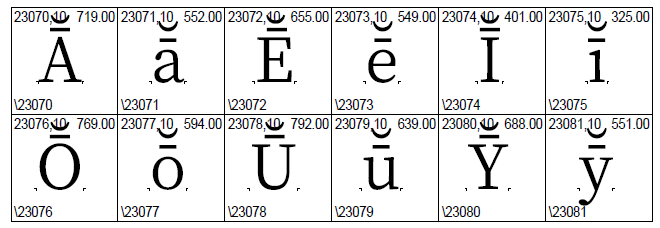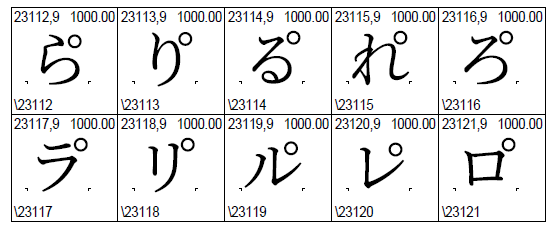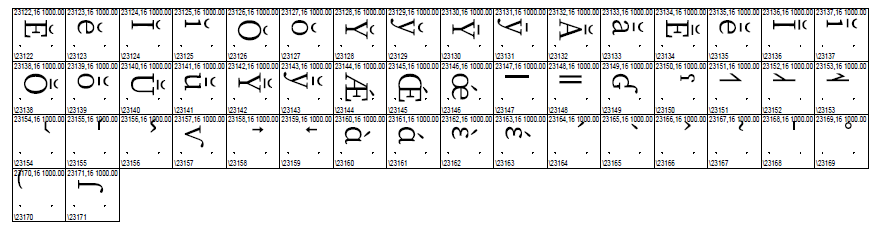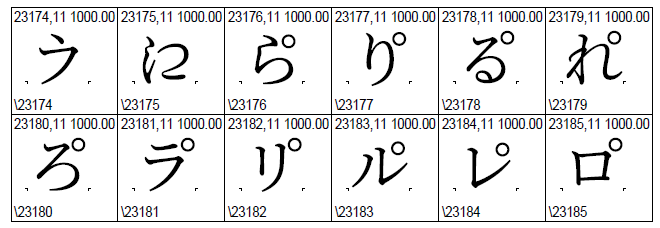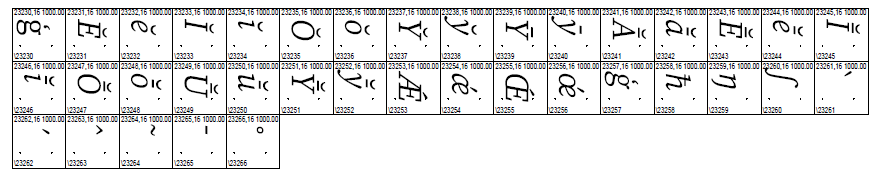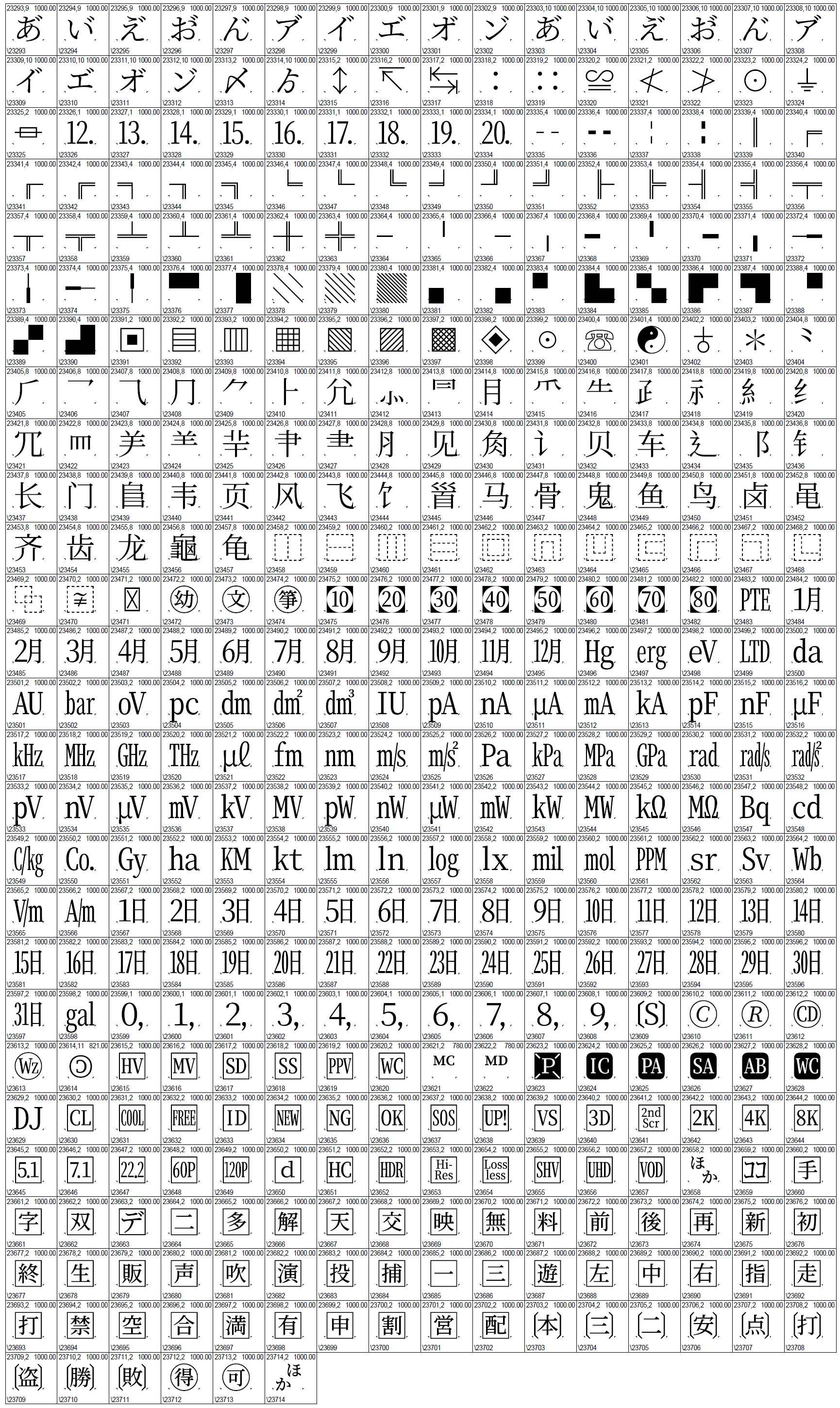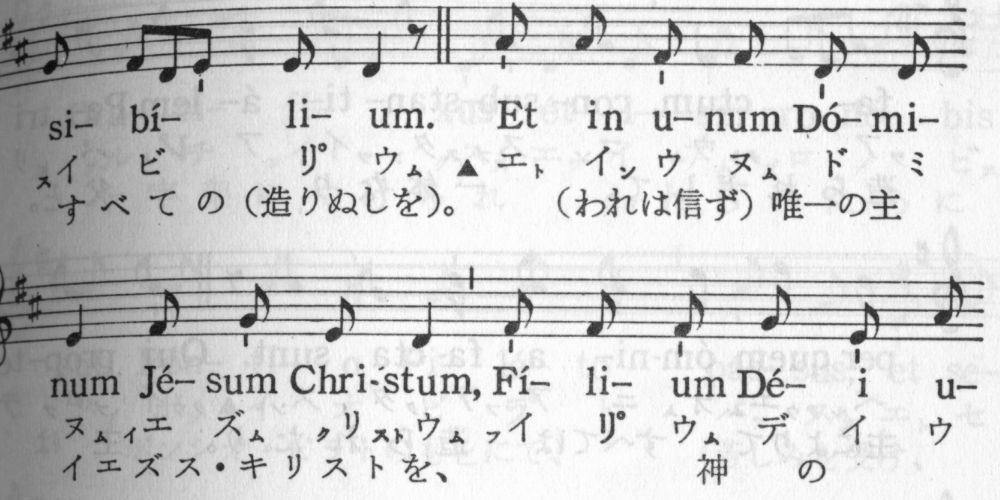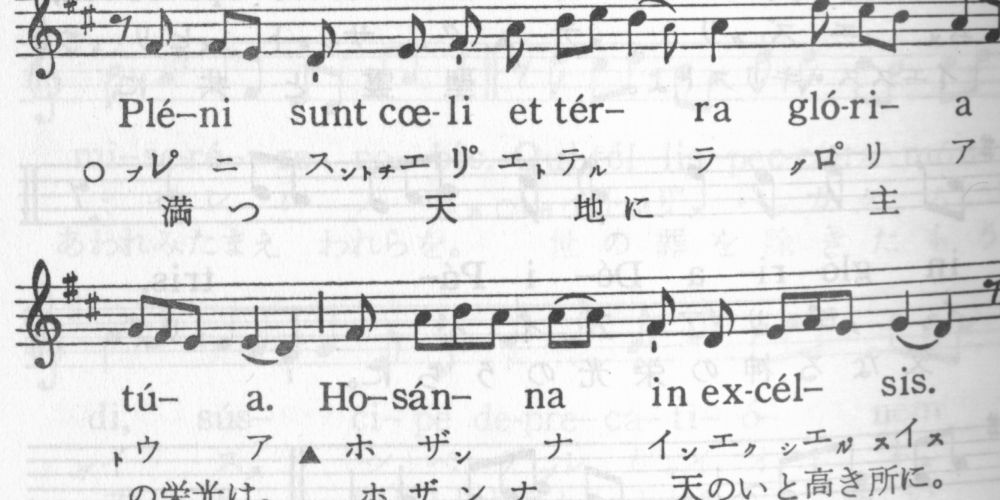
2020年8月更新分より、錦明朝およびその派生の錦源明朝、そして霧ゴシック、霧明朝はCIDの並びが共通化されてAdobe-Japan1-7の上位互換となっています。ただしAdobe-Japan1は独自拡張を認めていないことから、ROSはAdobe-Japan1を名乗らず現時点ではAdobe-Identity-0にしてあります。将来的には独自のROS名にする可能性もあります。
このグリフ集合の関連情報を以下にまとめました。
この範囲は前述したフォントすべてでAdobe-Japan1-7に準拠したCIDの並びになっていますが、現時点ではどのフォントもCID+0からCID+23059までをフルサポートはしていません。
グリフがないCID番号はUnicode値との紐付けを解除して、対応していない文字が空白で表示されたり豆腐に化けたりせぬようにしてあります。
Adobe-Japan1-7に含まれている仮名文字用グリフは、次の8種類に分類されます:1) 既定のもの、2) 縦書き用の小さな仮名(「っゃゅょ」など。横書き用は下のほうへ寄せてあるのに対して縦書き用は右のほうへ寄せてある)、3) 横書き専用デザインのもの、4) 縦書き専用デザインのもの、5) プロポーショナルな横書き専用、6) プロポーショナルな縦書き専用、7) ルビ用(縮小されることを見越してあらかじめ太めに作ってある)、8) 半角。
このうち 1), 2), 8) の3種類がもっとも古くからあるもので、他は後にSupplementとして追加されたものです。
Adobeが提供しているAdobe-Japan1用のGSUBテーブルにおいて、縦書き時に既定のグリフが自動的に縦書き用グリフへと切り替わるよう指示されているのは小さな仮名のみです。つまり 1) → 2) という置換のみが「義務的」です。それ以外の仮名文字では、縦専用グリフの使用は任意となっていて、4) に置換するにはvknaや、hkna+vert/vrt2を使って明示的に切り替える必要があります。
これに対して源ノ角ゴシック・源ノ明朝では、仮名文字用グリフは a) 既定兼横書き用、b) 縦書き用、c) 半角の3種類に整理されていて、プロポーショナルなグリフは a) または b) の両端の余白をpalt(横書き時)ないしvpal(縦書き時)でカットすることによって実現しています。
そして縦書き時には、vert/vrt2によってすべての仮名文字が常に縦書き用グリフへと自動的に置換されるようになっています。
霧ゴシック・霧明朝ともに、派生元である源ノ角ゴシック・源ノ明朝の仕様を受け継ぎつつAdobe-Japan1の仕様にも合わせるため、仮名グリフについては次のように処理しました。
即ち 1), 2), 4) にはすべてグリフが割り当てられていて、逆に 3), 5), 6), 7) は空っぽの状態です。このうち 3) は a) を流用することで、そして 5), 6) についてもpalt, vpalの情報を使ってグリフを作り出すことで、それぞれ埋めることも一応可能ではありますが、デザインに差異がない以上、同じグリフを複数のCIDに割り当てても単にフォントサイズを膨らませる結果にしかなりませんので、現時点では見送ってあります。
2020年8月現在、CID+23058~23059 (U+32FF) は霧ゴシックにのみグリフが入っています。源ノ明朝でこの字を含む版がリリースされ次第、霧明朝、錦源明朝にも含める予定です。
Adobe-Japan1-7の続きの部分です。主に語学や音声学に関するものが入っています。この範囲は前記4フォントファミリーすべてで対応しています。
詳細は次の通りです。
それぞれ E/e, I/i, O/o の上にブレヴェ (breve) と呼ばれる記号を乗せたものです。母音にブレヴェを乗せたグリフのうち、A/aとU/uとはAdobe-Japan1に含まれていますが、E/e, I/i, O/oは含まれていません。 なお最後の2字、O/o の上にブレヴェを乗せたものだけは、源ノ角ゴシック (Source Han Sans) と源ノ明朝 (Source Han Serif) にも含まれています。 |
それぞれ Y/y の上にブレヴェ、マクロン (macron) と呼ばれる記号を乗せたものです。ラテン語では Y/y は母音字であることから、長短の区別を示す際にこれらの記号が付与されることもあります。 |
それぞれ A/a, E/e, I/i, O/o, U/u, Y/y の上にマクロン (U+0304) を乗せ、さらにその上にブレヴェ (U+0306) を乗せたものです。ラテン語を綴る際、「長母音としても短母音としても発音される」ことを示すのに使われます。 |
それぞれ Æ (U+00C6), Œ, œ の上に鋭アクセント(アクサンテギュ)を乗せたものです。こちらもラテン語(主に教会ラテン語・中世ラテン語)で使われることがあるので収録しました。 ラテン語用グリフはここまでです。 |
ここからはIPA記号です。
IPA公式サイトにあるUnicode値付きのチャートの2段目、CONSONANTS (NON-PULMONIC) という表の左の列には、吸着音 (Clicks) と呼ばれる記号が5つ縦に並んでいます。このうち1番上のU+0298と、下からの2番目のU+01C2とはAdobe-Japan1-7に収録済みです(それぞれCID+15820、CID+15821)。 残ったU+01C0とU+01C1とについては、それぞれ | (U+007C) および‖(U+2016) のグリフを流用することも検討しましたが、これらのグリフはステムの幅や高さがU+01C2と著しく異なっていて並べた時に統一感がないことから、U+01C0とU+01C1とには別CIDを割り当てました。 |
JIS X 0213が正しく対応し損ねたと思われる文字その1です。JIS X 0213の表では大文字のGをベースとしたグリフで示されていることもあり(1面11区9点)、大半のフォントではƓ (U+0193) にマッピングされています。 しかし同表でこの付近(1面11区)に配置されている文字はいずれもIPA記号であることを踏まえますと、JIS X 0213が本当にサポートしたかったのはIPA記号のU+029B(グリフの高さがx-height相当のもの≒スモールキャピタルのGがベースであるグリフ)であったのではないかと推察されます。 IPAの公式チャートに載っている記号は一通り対応するという方針の下、このU+029Bも不足分を補うため収録しました。 |
こちらはAdobe-Japan1が正しく対応し損ねたと思われる文字です。Adobe-Japan1の表でCID+15897は次のようなグリフで示され、かつCMapではU+02C1と結びつけられています。
しかしこのCID+15897のグリフのように、縦ステムの底部に下駄のようなものがあるのは、Unicodeの表ではU+02C1ではなくU+02E4のほうです。
Unicodeの表でU+02E4は「Additions based on 1989 IPA」という見出しの下にあり、IPA記号であることが分かります。対してU+02C1は「Miscellaneous phonetic modifiers」という見出しの下にあり、「IPA記号風の何か」に過ぎぬらしいことが分かります。 |
IPAのトーン記号です。それぞれ high rising, low rising, rising-falling を表すdiacriticsおよび音調曲線です。JIS X 0213に入らなかった経緯は不明です。1989年版のIPAチャートにも掲載されていますので(右下)、少なくとも規格策定当時まだなかったという理由ではなさそうです。 |
2005年に追加されたIPA記号です。JIS X 0213やAdobe-Japan1-6制定時にはまだなかったためどちらにも入っていません。 |
再びIPAのトーン記号です。 |
JIS X 0213が正しく対応し損ねたと思われる文字群その2です。1面11区38-39点および48-49点は、ほとんどの日本語フォントでそれぞれギリシア文字のU+1F70, U+1F71, U+1F72, U+1F73にマッピングされています。しかしこの付近の文字は基本的にIPA記号ですので、本当にサポートしたかったのはIPA記号であるU+0251とU+025Bとの上に、それぞれU+0301とU+0300とを乗せたものであったのではないかと判断し、これらを改めて追加しました。 CID+9419~9420、CID+9433~9434を再利用して多重マッピングにしなかったのは、ラテン文字ベースのIPA記号とギリシア文字とでは、グリフのデザインが微妙に異なっているケースも少なくないためです(特にU+0251のɑとU+03B1のα)。 |
Adobe-Japan1では幅ありのdiacritics (U+02B0~U+02FF他) と、合成を前提とした0幅のdiacritics (U+0300~U+036F) とで同じグリフを共有しているケースがあります。例えばCID+65のグリフは、「U+0060, U+02CB, U+0300」という3つのコードポイントと結びつけられています。
この状態が少し気になりましたので、「IPA表に掲載されているもの」に限って先のような包摂を解除し、合成を前提とした0幅のdiacritics (U+0300~U+036F) のほうには別CIDを割り当てました。
なおこれに関連して、Adobe-Japan1のチャートでは「幅ありグリフ」で例示されているCIDでも、それが0幅文字(U+0300~U+036Fの範囲)にのみマッピングされている場合は、独自に0幅グリフに置換しました。具体的には次のものが該当します。
Adobe-Japan1において幅ありのdiacriticsと、0幅のdiacriticsとがグリフを共有している例は他にもありますが、「IPA表に掲載されているもの」という条件を満たさないものについては今回は何もしませんでした。 |
| 23108: 035C |
JIS X 0213が正しく対応し損ねたように思われる文字その3です。JIS X 0213の1面11区56点(音符のタイのような記号)は大抵の場合、U+203Fに結びつけられていますが、この文字は「1面11区50点(=U+0361)とペアをなしているようであること」「この付近はIPA記号が集まっていること」を踏まえますと、本当はU+035Cとマッピングされるべきものであったのではないかと考え、新規に追加しました。 IPA記号の補完はここまでです。 |
| 23109: 017F |
小文字のsを縦に引き伸ばした文字です。OCRでは誤ってfとして読み取られてしまっているのをよく見かけます。 |
|
23110: 1B000 23111: 1B001 |
当サイトのメインです。 |
|
23112: 3089+309A 23113: 308A+309A 23114: 308B+309A 23115: 308C+309A 23116: 308D+309A 23117: 30E9+309A 23118: 30EA+309A 23119: 30EB+309A 23120: 30EC+309A 23121: 30ED+309A |
それぞれ「らりるれろラリルレロ」に合成用半濁点 (U+309A) を重ねたものです。外来語のL音を表記するために考案されたもので、国会図書館のデジタルコレクションの中にちょくちょく用例が見つかります。 例1aと1b、 例2、 例3、 例4aと4b、 例5、 例6(ひらがな)。
いわば外来語表記用に考案された仮名として「ヴ」ほどには世間に浸透せず、いつしか忘れられてしまったものとも言えます。同じように忘れられてしまった仮名としては濁点付ワヰヱヲというものもありますが、こちらはAdobe-Japan1に収録されています(CID+8313から8316)。 もう少し日の目を見てほしいと思いフォントに収録しました。 |
| 23122-23171 |
ここからは縦書き時に使用されることを意図したグリフです。 |
| 23172-23173 |
合成用の濁点 (U+3099, CID+16326) および同半濁点 (U+309A, CID+16327) の縦書き時用グリフです。 それに対して上の縦書き用グリフは、グリフのadvance height(「送り幅」ならぬ「送り高さ」)を0にした上でVORGを-120に設定することにより、直前の(真上の)グリフに重ねて描画されるように作ってあります。 源ノ角ゴシック・源ノ明朝ではGPOSとvertとを組み合わせ、既定兼横書き用グリフを直接右上へ移動させることで縦書きに対応させようとしています。しかしこのようなvertの使い方はOpenType仕様書に記載がなく、期待通りの動作をする環境は少ないのではないかと思われますので、従来からあって仕様書にも載っているGSUBを使った方法で適切なグリフに切り替わるようにすべくCIDを割り当てました。 これらのグリフを利用した合成は、直前の文字が何であれ濁点や半濁点を打つことが出来るというメリットがある反面、あくまで機械的に重ね描きするだけであることから、既に線が描画されているところに濁点や半濁点を描いてしまうことも起こり得るというデメリットがあります。そのため合成済みのグリフが用意されていない組み合わせ限定で使われるようにしてあります。 |
| 23174-23185 |
CID+23110から23121までの12グリフの縦書き版です。 錦明朝(派生の錦源明朝も含む)は小さな仮名(「っゃゅょ」など)を除いて、縦書き専用の仮名グリフというものを現時点では持っていません。そのためこの範囲にも何も入っていません。 |
|
23186: FFF9 23187: FFFA 23188: FFFB 23189: FDD0 23190: FDD1 23191: FDD2 23192: FDD3 |
拙作のSolstitiumに渡すテキストを編集する際、これらのコードポイントにグリフがあると便利なことからフォントに入れてあります。
最初の3つはそれぞれ「ルビ対象文字列開始」「ルビ開始」「ルビ終了」を表します。 |
2020年秋に増補した部分です。この範囲のグリフは現時点では霧ゴシックと霧明朝のみがサポートしています。ただもし時間と気力の都合が付くようであれば、いつか錦明朝および錦源明朝にも含められたら良いなと思い、あえて次のブロックとは切り離して配置してあります。
詳細は次の通りです。
| CID値: Unicode値 | 解説 |
|---|---|
| 23193: 0123 |
ここまでの追加により、結果として Latin Extended-Aブロック(U+0100~U+017F)で対応していないのはこの文字だけになったこと、そして対となる大文字 (U+0122, Ģ) は既にSupplement 6 (CID+20336) で追加されていることとを踏まえてこの字も含めました。 |
| 23194-23216 |
CID+23060~CID+23082のイタリックグリフです。 |
| 23217 |
U+01FD/ǽ (CID+9421) のイタリックグリフです。1つ前、CID+23216の小文字に相当するものです。 |
| 23218-23219 |
CID+23083~CID+23084のイタリックグリフです。 |
| 23220-23223 |
それぞれ U+0123/ģ (CID+23193), U+0127/ħ (CID+15816), U+014B/ŋ (CID+9436), U+017F/ſ (CID+23109) のイタリック体グリフです。ここまでの追加により、Latin Extended-Aブロック(U+0100~U+017F)でイタリック体グリフがないのはこれら4文字のみとなったので含めることにしたものです。 |
| 23224-23229 |
それぞれCID+23102~CID+23107(U+0300~0304, 030A)のイタリック体グリフです。 |
| 23230-23266 |
ここまでに出てきたCID+23193~CID+23229の縦書き用グリフです。 |
| 23267-23269 |
それぞれ U+0268/ɨ (CID+15827)、U+029D/ʝ (CID+15811)、U+012F/į (CID+20357) の上部の点を取ったものです。i (CID+00074)、j (CID+00075) から点を取ったものは既にAdobe-Japan1に含まれています(それぞれCID+00146、CID+09435)。 |
| 23270-23271 |
それぞれ U+0237/ȷ (CID+09435)、CID+23269のイタリック体グリフです。U+0131/ı (CID+00146) のイタリック体グリフは既にAdobe-Japan1に含まれています (CID+09589)。 上のCID+23267~23268については、IPA記号にはイタリック体グリフを用意しないというAdobe-Japan1の慣例に従って現時点ではイタリック体グリフを含めてありません。 |
| 23272-23276 |
CID+23267~CID+23271までの縦書き用グリフです。 |
| 23277-23278 |
それぞれ合成用の囲み白丸 (CID+16328, U+20DD) と白い四角形 (CID+11035, U+20DE) の縦書き用グリフです。合成用濁点・半濁点と同じ理由により、縦書き用グリフを別途用意してCIDを割り当てました。 |
|
23279: 301A 23280: 301B |
U+301AとU+301Bとです。 |
| 23285-23286 |
CID+23279~CID+23280の縦書き用グリフです。 |
|
23281-23284 23287-23290 |
この範囲は意図的に空けてあります。 |
この範囲のグリフは霧ゴシックと霧明朝のみがサポートしています。
それぞれの派生元である源ノ角ゴシック、源ノ明朝ともに収録している文字のうち、Adobe-Japan1-7になく、かつここまでの表にも含まれていないものをこの範囲にまとめて配置しました。ただし両フォントに含まれているグリフでも、日本向けではないと思われるものは除外しました。
詳細は次の通りです。濁点付きひらがなや康煕部首、ARIB記号と思われるものなどが主です。
| CID値 | 解説 |
|---|---|
|
23293-23312 23315-23714 |
グリフ数が多いのでCIDとUnicode値との対応表は別ファイルにしてあります。 特記事項のあるグリフのみこの下で別途取り上げます。 |
|
23291: 3031 23292: 3032 |
それぞれU+3033/U+3034とU+3035とを結合済みの状態にしたものです。 |
| 23313-23314 |
それぞれ〆 (CID+658, U+3006)、ゟ (CID+12181, U+309F) の縦書き用グリフです。Adobe-Japan1ではこれらに対して縦書きグリフ用のCIDを割り当てていないよう(プロポーショナルならあり)でしたので、ここに配置しました。 |
源ノ角ゴシックまたは源ノ明朝の片方にしか含まれていないグリフについては、U+32FFを除いてすべて霧ゴシック・霧明朝には継承させませんでした。この種のグリフはゴシック側に2つ(version 2.001でのCIDが2649と35833)、明朝側に1つ(version 1.001でのCIDが16082)あり、いずれも康煕部首または部首補助ブロックの文字用です。
これらのグリフと紐付けされていたUnicode値に対しては、含んでいない側のフォントやAdobe-Japan1のマッピングを参考にして、別のグリフを代わりに割り当ててあります。
2020年秋の増補ではCID+23193以降をCID+23291以降へずらし、空いた空間に新規グリフを配置しましたが、今後新しいグリフを追加する時は途中に差し込まずCID+23715以降に置く予定です(具体的な追加候補は今のところありません)。
ただしAdobeがAdobe-Japan1-8をリリースし、個人的に欲しいグリフがそこに含まれていた場合に限っては、Adobe-Japan1-8準拠に再度CIDを振り直す可能性もあります。